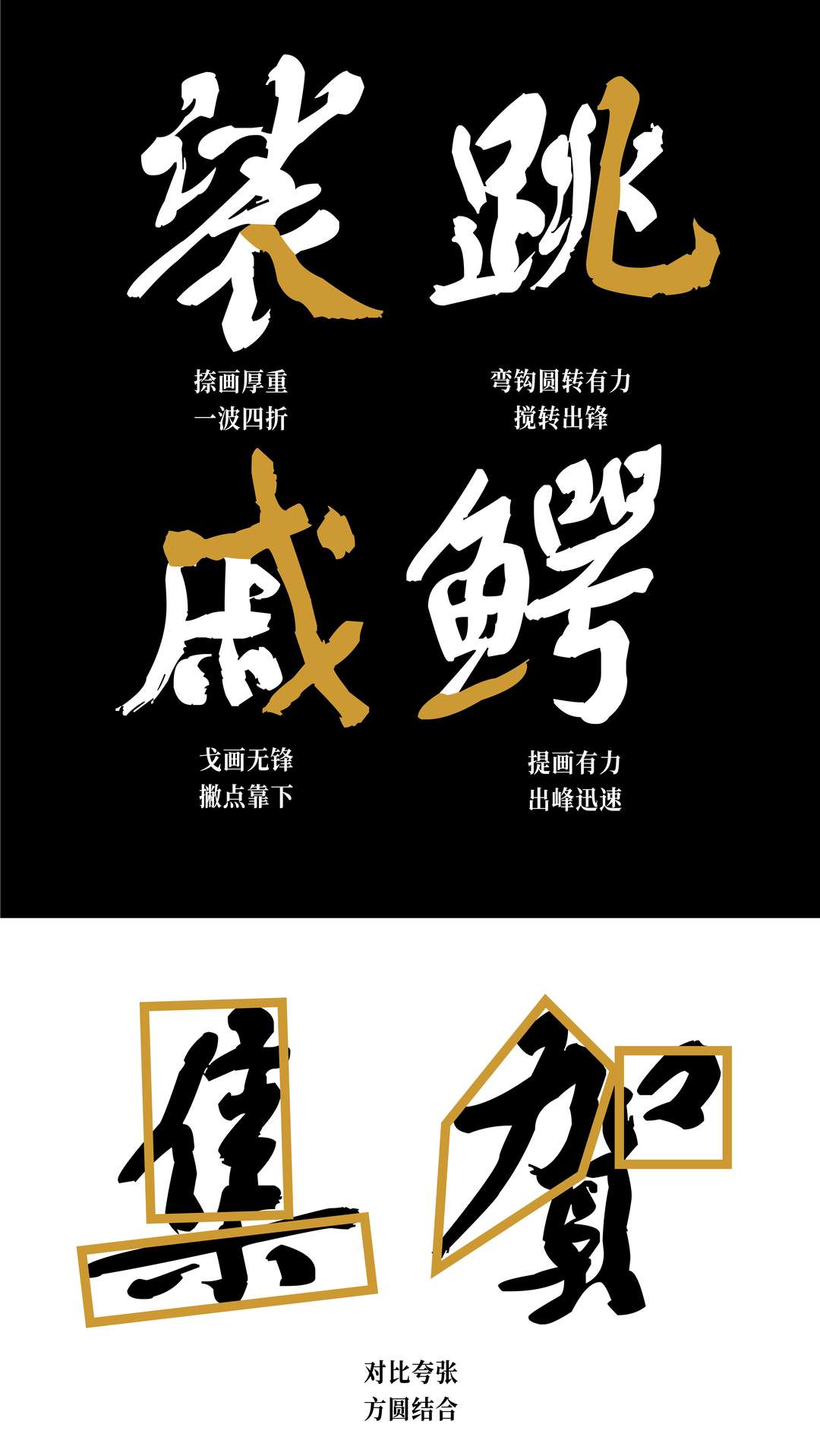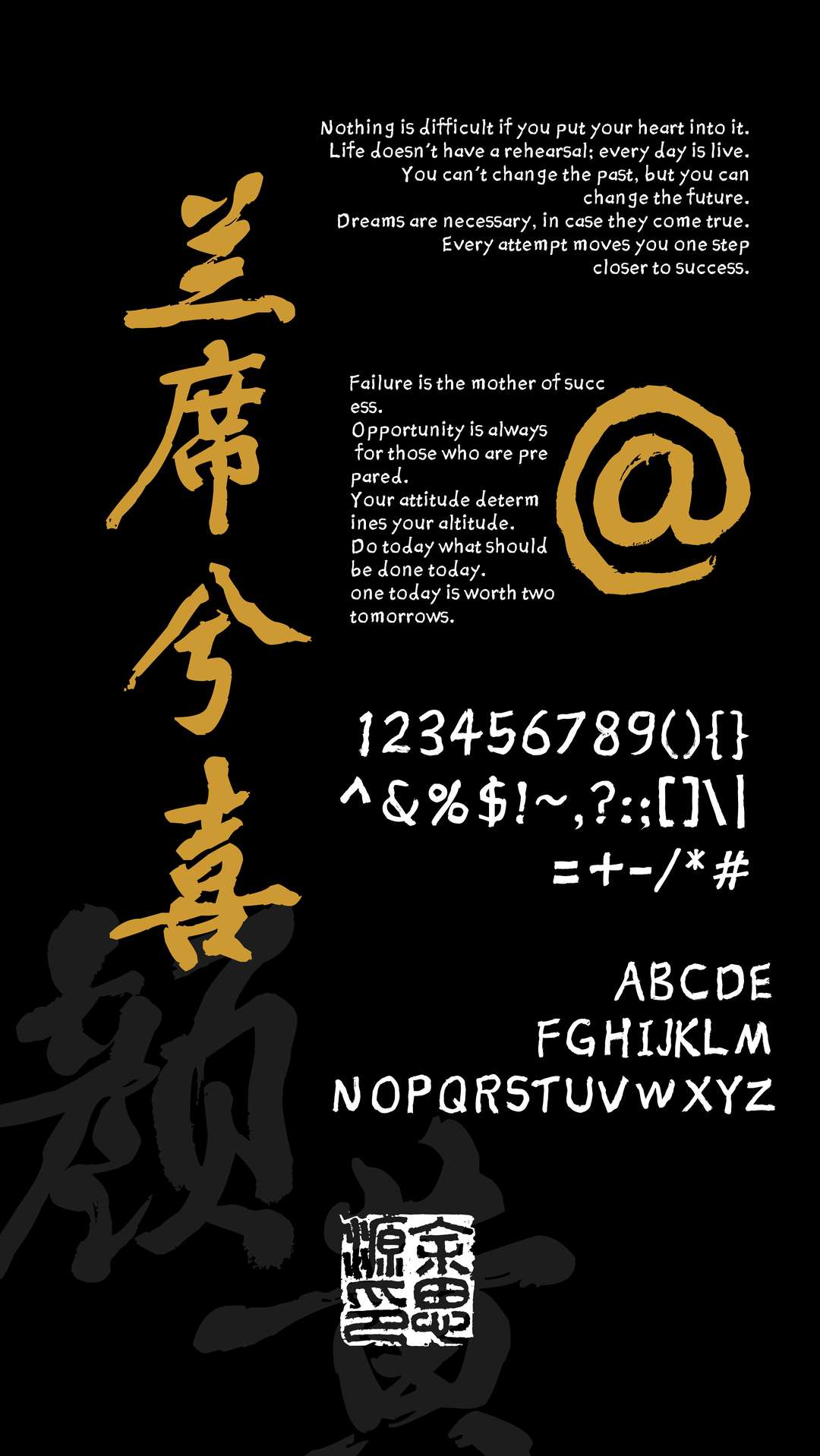
| 字体作者:余思源 (中国大陆) | 字体字重:1个 |
将中唐大书法家颜真卿的书法特点与宋四家之一的黄庭坚的风格结合。颜真卿筋骨的厚重感与黄庭坚的长枪大戟融为一体,实现浑厚酒脱的行楷风格。用笔上保留个人书写习惯的同时表现外拓厚重、撇捺舒展、横画千里阵云等特点,让字体有较强的书法气息又不失设计感。字体强调书法的传承也兼具现代设计的需求。
余思源颜黄体相较于如今市面上的行楷书法字体线条粗细适中,笔法中变化丰富,方圆结合保留了许多字体飞白又不像江湖体般张牙舞爪,辨识度较强,是一款拥有简体中文繁体中文与英文希腊等符号的一款较为完整的行楷书法字体,适用于多类设计场合。
有汉字、西文上万字的原创字体很不容易,可惜存在不少技术问题影响了使用:
BDFZ(北大方正)显然有问题,作者自己是否考虑过厂商ID?如无可留空。〩字形并非“攵”形需重写,这有统一码范本。kern,如作者给的展示图中“STAFF”的“TA”分太开仿佛夹了空格,“AFF”又太挤。¢£‾¥与¢£ ̄¥复用同全角字形,这不应该。如果能允许我重新编辑,也许能改善这些问题。
细节很丰富,适合做大字用,细节度拉满。小字用的时候反而因为不够圆润,感觉略糟糕。
这款字体好全!大赞